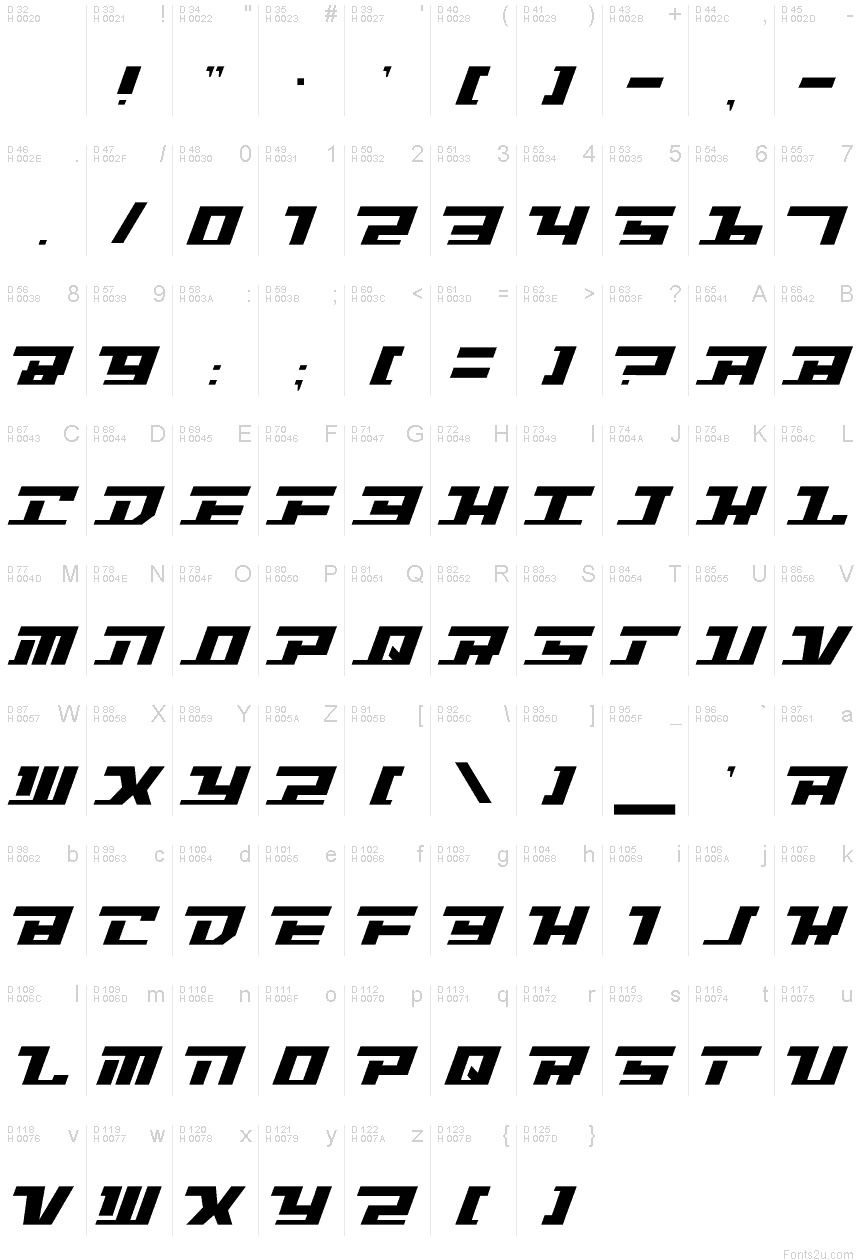
Intrepid od Iconian Fonts to darmowy krój displayowy w stylu techno, który wygląda, jakby był w ciągłym ruchu. Każda litera jest dynamicznie pochylona, co sprawia, że słowa zdają się mknąć po ekranie. Wąskie światła między znakami i ostre cięcia nadają mu elektryzującą energię, kojarzącą się z prędkością, obwodami i adrenaliną.
Intrepid to idealny wybór, gdy chcesz, aby nagłówki nabrały charakteru na plakatach sci‑fi, logotypach wyścigowych, tytułach gier, w brandingu esportowym, nakładkach streamingowych czy bannerach technologicznych. Ten darmowy font najlepiej prezentuje się w dużych rozmiarach, gdzie jego ostre krawędzie i długie poziome linie mogą w pełni wybrzmieć. Dla zachowania równowagi, zestaw Intrepid z prostym, geometrycznym krojem bezszeryfowym w tekście głównym i pozwól nagłówkom przejąć całą uwagę.